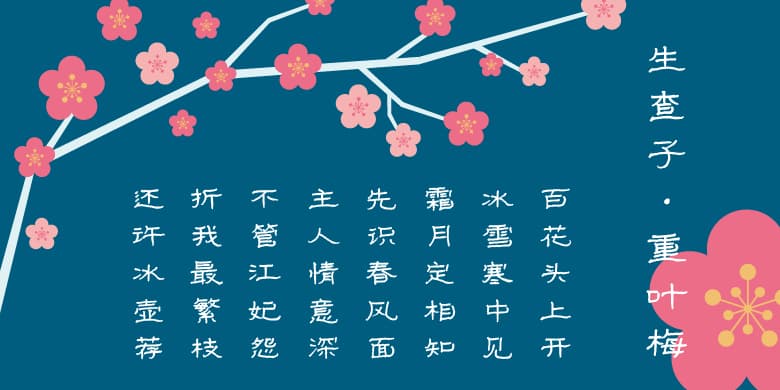
品牌:方正字迹设计师:张惟梓发行时间:2020字库编码:大陆简体(GB2312-80)分类:常规书写·硬笔字体属性:精品字
该款隶书取法汉隶名帖《礼器碑》,用硬笔书写,笔画更加瘦劲,线条更加凝练。将笔画的粗细、方圆,笔势的动静、向背完美地统一在一起。其结体严谨,字法规范,清超遒劲,庄重典雅,高古且充满逸趣。适用于文化类产品的包装宣传设计等。
作者张惟梓,擅长绘画、摄影及美术字设计等,长期从事企业文化、宣传及产品设计开发工作,摄影及美术作品曾多次参加省市级展览。